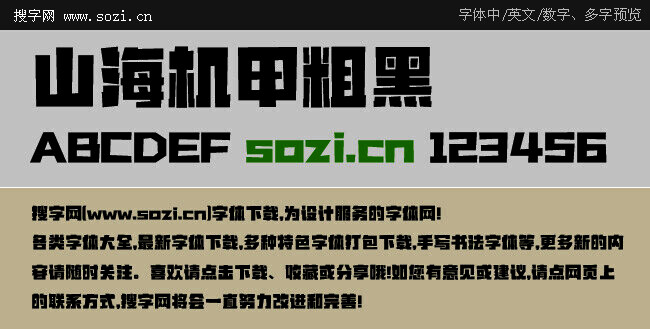
山海機(jī)甲粗黑
搜字網(wǎng)提供一款山海機(jī)甲粗黑中文藝術(shù)字體下載,山海機(jī)甲粗黑是一款綜藝標(biāo)題黑體字體,包含簡(jiǎn)體漢字6763個(gè)。該字體是一款具有強(qiáng)勁視覺沖擊力的綜藝風(fēng)格標(biāo)題字體。字形充實(shí)填滿整個(gè)字框,造型硬朗,全直線的筆畫構(gòu)成棱角分明、堅(jiān)實(shí)有力。適合包裝設(shè)計(jì)、海報(bào)設(shè)計(jì)、廣告設(shè)計(jì)等應(yīng)用。